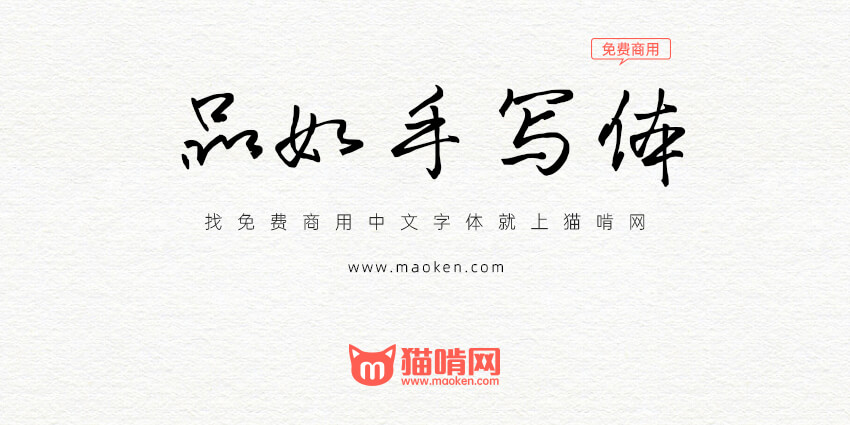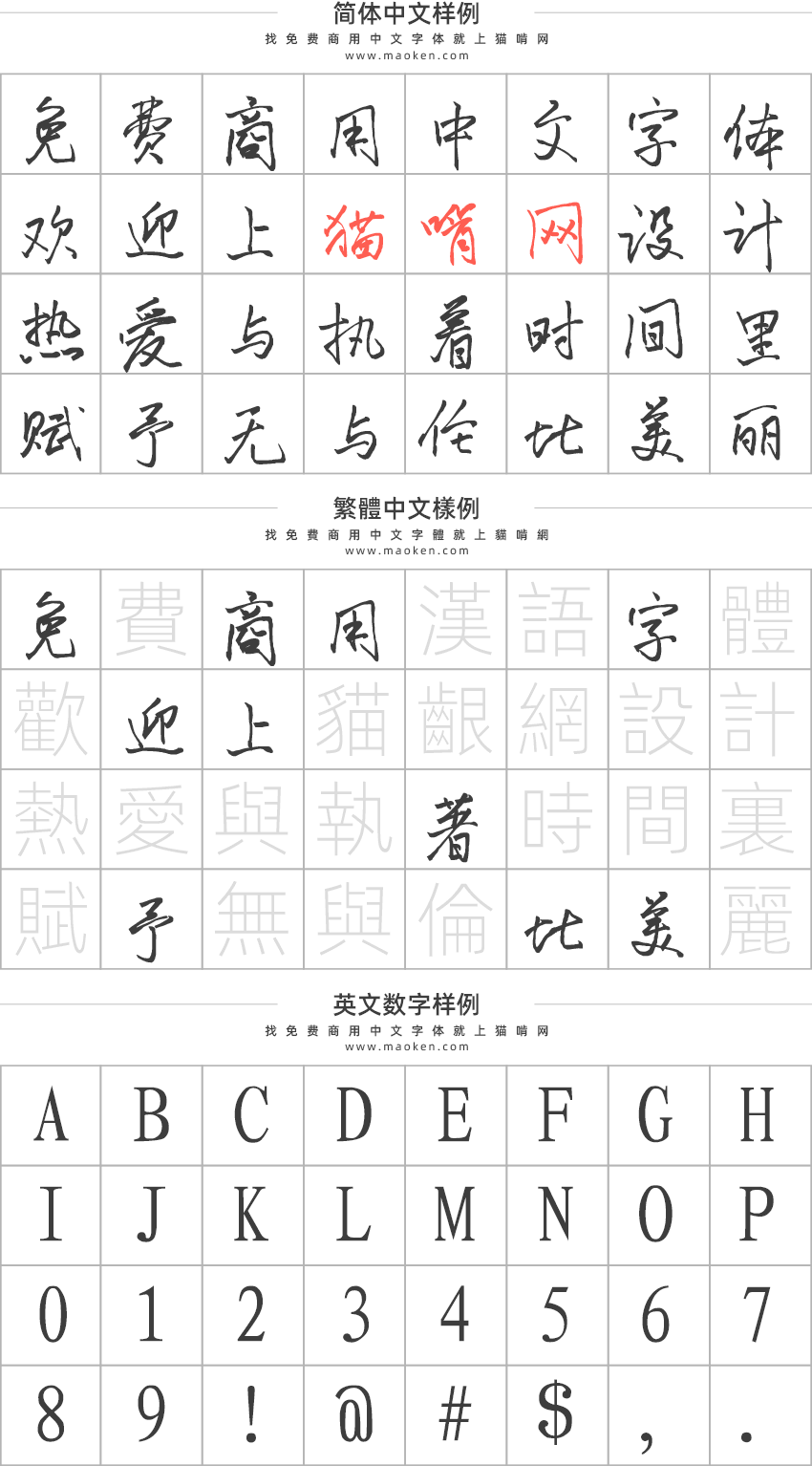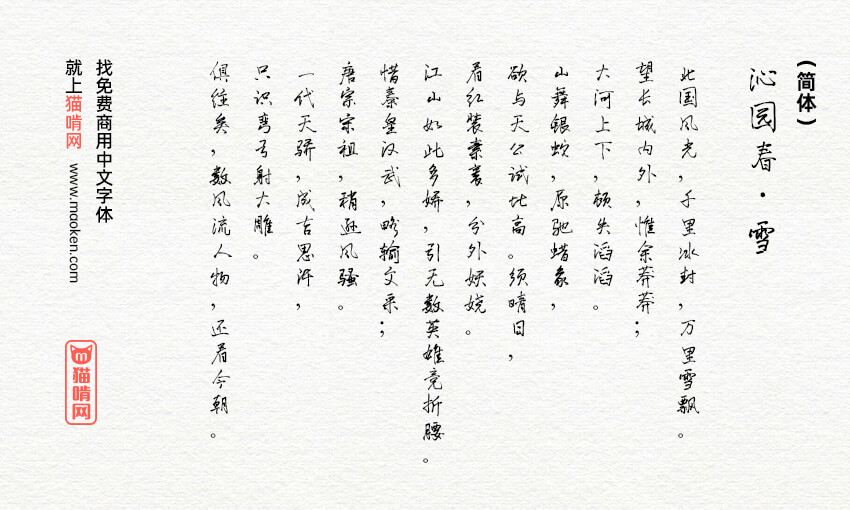
品如手写体:一款永久使用可免费商用的手写字体
字体作者:林芳柽 (中国大陆) 字体字重:1个
这些年下来,许多字体都开始收版权费,十分苦恼! 自己是个书法爱好者,索性写一套自己的字库,想到就去做了。然后,历时半年时间,利用业余时间,写了这套字库,命名为品如手写体。
作者林芳柽,品如设计创意总监 淘宝装修市场专属讲师。曾任职于国际知名4A广告公司奥美,服务过奔驰、三菱、网龙、中国移动等知名客户。受阿里巴巴邀请参与撰写智库新书《全网诚信通》。
这个帖子发布之后的四五年里,我便忙其他事情去了,所以我自己并没有太关注。
然后我自己百度搜索了一下我这个品如手写体,发现居然被很多字体平台和爱好者广为流传,心里颇为矛盾,一边感到很欣慰,一边又觉得有点惭愧!
欣慰,是因为自己花了那么多时间写的字,有人喜欢,并且使用,我觉得个人的价值得到了体现。
惭愧,是因为当时制作字体用了一个三方软件,通过手绘板进行书写,很容易打滑,很难发挥水平,而且笔划也是电脑模拟的,不真实,因此,自我感觉这个字体水平不高,粗糙了一些,但还算率真。